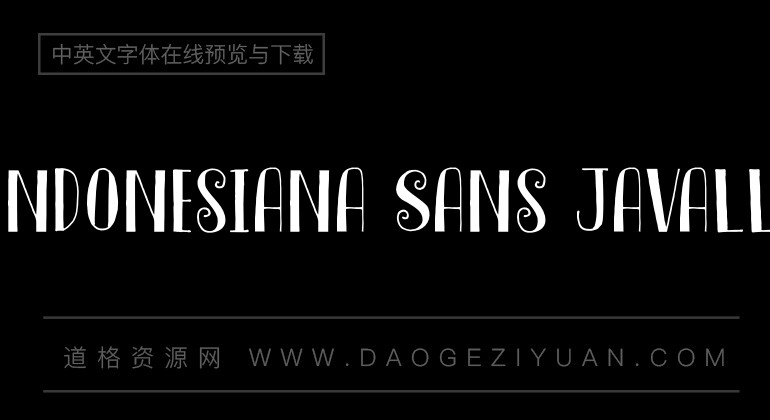
FTF Indonesiana Sans Javallonia 是一款印尼风格的无衬线字体。它是由菲律宾字体设计师Ferry Hadriyan创建的,最初是为了纪念印度尼西亚独立日而设计的。 该字体的设计灵感来自印度尼西亚传统艺术和文化,展现了该国的多样性和独特性。它的字母形状和线条都非常流畅,具有很高的可读性和视觉吸引力。字体中使用的一些元素也与印度尼西亚文化有关,比如借鉴了传统印度尼西亚文化中常用的纹样和装饰。 FTF Indonesiana Sans Javallonia 字体适用于设计印度尼西亚文化、艺术和旅游相关的材料。它也可以用于印度尼西亚文化和历史方面的教育项目。内容介绍
FTF Indonesiana Sans Javallonia是一款非常不错的手写艺术字体,具有很好的视觉感,适合于文化类的宣传设计、商业类品牌的广告和产品包装设计以及个性化文字排版等较多场景。